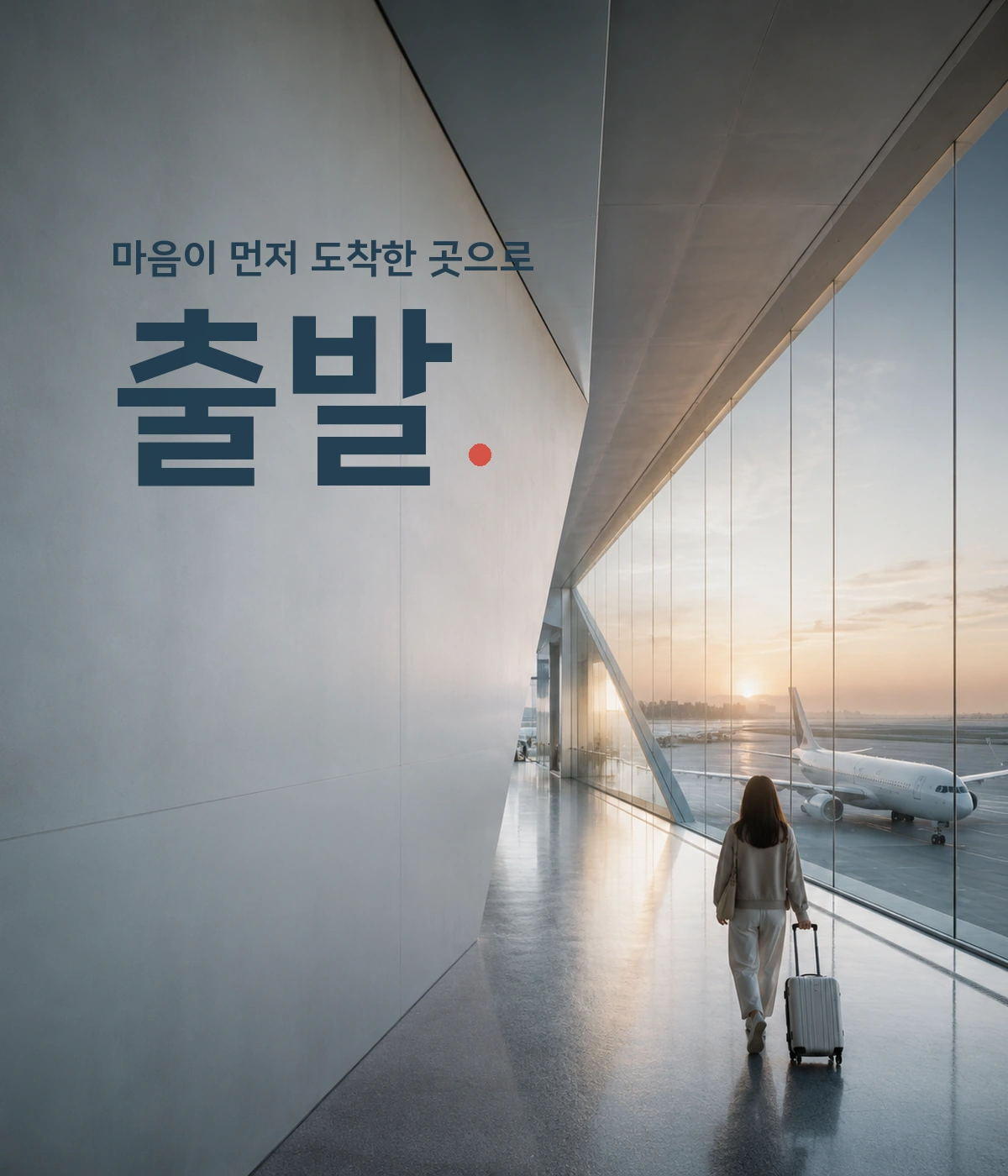
티웨이 날다체 — 티웨이 X 폰트랩(주)에서 배포하는 무료 폰트입니다. 직선적인 자소와 정방형 구조에 비행기 날개의 이미지를 담은 밝고 단정한 고딕체
티웨이항공 서체 세 벌 가운데 브랜드와 장식을 맡는 쪽입니다. 2021년 3월에 폰트랩과 함께 공개됐습니다.
같은 가족 안에서 골격이 다릅니다. 제목용인 항공체가 장방형이라면 이 서체는 정방형에 가깝습니다. 제작사는 정방형의 느낌으로 비행기 날개와 티웨이항공의 고객 중심 아이덴티티를 살린 모습이라고 설명합니다. 굵은 디스플레이 계열에서 파생됐지만 돌기를 단순화해 인상이 너무 강해지지 않도록 조절했습니다.